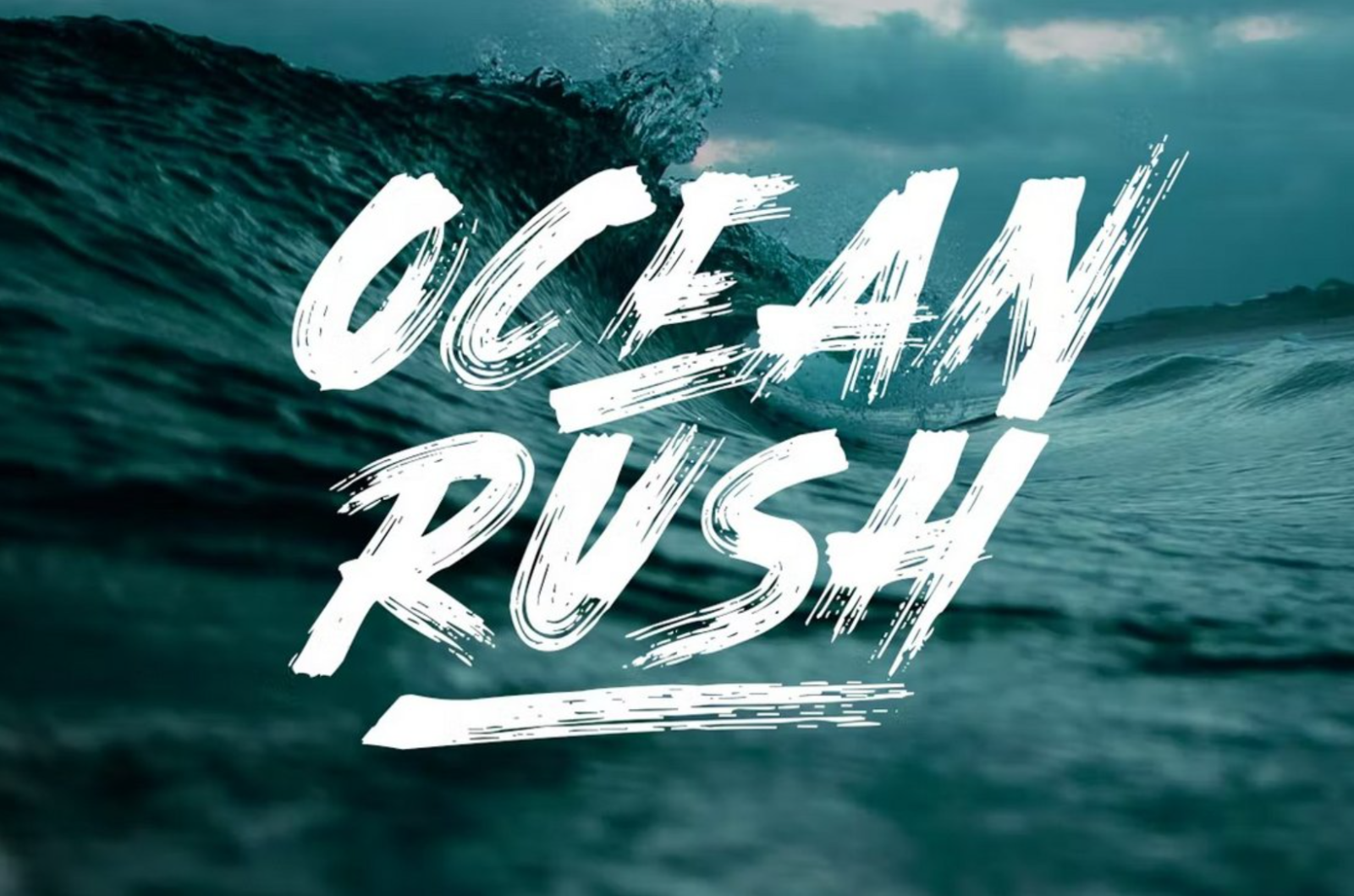
10 Font Viết Tay "Chất Lừ" Không Thể Thiếu Trong Thiết Kế Của Bạn
Dù bạn là người mới bước vào nghề hay là designer kỳ cựu, những font chữ viết tay “chất phát ngất” này chắc chắn sẽ khiến bạn không thể rời mắt. Tham khảo ngay danh sách và làm mới thư viện font của bạn!
Trong thế giới thiết kế đầy màu sắc, font chữ luôn đóng vai trò then chốt quyết định phong cách và cảm xúc của sản phẩm. Trong đó, font chữ viết tay (handwritten fonts) ngày càng được ưa chuộng khi mang đến sự cá tính, ấm áp và gần gũi. Một nét chữ vẽ tay không chỉ giúp thương hiệu của các bạn có dấu ấn riêng biệt mà còn truyền tải cảm xúc chân thật và tự nhiên hơn. Bài viết này, SaDesign sẽ giới thiệu tới bạn Top 10 font viết tay phổ biến nhất hiện nay, kèm theo tiêu chí lựa chọn cũng như mẹo phối hợp và nguồn tài nguyên để bạn có thể tự tin “rinh” về và sử dụng ngay trong thiết kế của mình. Hãy cùng khám phá nhé!
1. Tiêu chí lựa chọn font chữ viết tay
Trước khi điểm qua 10 font nổi bật, chúng ta cần hiểu những yếu tố then chốt giúp đánh giá và lựa chọn một font viết tay phù hợp:
Tính dễ đọc (Readability)
Một font viết tay có thể rất đẹp, nhưng nếu đọc không rõ trên các kích thước nhỏ hoặc nền phức tạp, nó sẽ mất đi giá trị thiết kế. Hãy ưu tiên những font có độ tương phản đủ, nét chữ rõ ràng để người xem không phải “vất vả” khi đọc.
Phong cách (Style)
Font viết tay rất đa dạng: từ nét tròn vui tươi, casual năng động đến các chữ nghiêng thanh lịch, tinh tế. Việc xác định phong cách của dự án ví dụ: trẻ trung, nữ tính, sang trọng hay tối giản sẽ giúp bạn thu hẹp lựa chọn nhanh chóng.
Độ đa dụng (Versatility)
Một font tốt nên hỗ trợ đầy đủ ký tự Latin (bao gồm cả dấu tiếng Việt), có nhiều trọng lượng (weight) hoặc biến thể (italic, bold) để dễ kết hợp khi cần nhấn mạnh.
Phù hợp với brand identity
Không phải font nào đẹp cũng phù hợp với nhận diện thương hiệu. Hãy cân nhắc tính cách và giá trị cốt lõi của thương hiệu: font viết tay nên phản ánh được tinh thần đó, tránh “lệch pha” khiến thiết kế trở nên thiếu tính nhất quán.
Khả năng phối hợp (Pairing)
Một font viết tay thường đi cùng một font serif/sans-serif để tạo tương phản. Khi phối font, hãy thử nghiệm tỷ lệ kích thước, cách canh lề và khoảng cách chữ (tracking/leading) để đảm bảo hài hòa.
2. Top 10 font chữ viết tay phổ biến nhất
Dưới đây là danh sách 10 font viết tay được nhiều Designer ưa chuộng, kèm mô tả, ứng dụng và nguồn tải để bạn dễ dàng “rinh” về dự án:
2.1. Amber Queen Signature
Amber Queen Signature là font viết tay Unicode mang tinh thần khám phá, hòa trộn giữa nét handcrafted và hơi thở hiện đại.
Đặc điểm nổi bật:
• Các góc chữ sắc, nét cắt dứt khoát tạo cảm giác cá tính mạnh mẽ.
• Độ nghiêng vừa phải giúp chữ liền mạch, không quá “lạng quạng”.
• Hỗ trợ đầy đủ ký tự Unicode, bao gồm tiếng Việt có dấu.
Ứng dụng gợi ý:
• Logo cá nhân, chữ ký số hóa trên website.
• Tiêu đề poster, bìa sách về du lịch, khám phá.
2.2. Leah Gaviota Hand Lettered
Leah Gaviota Hand Lettered là bộ font đa dạng, kết hợp giữa chữ đậm, sans‑serif và script để tạo nên phong cách độc đáo.
Đặc điểm nổi bật:
• Bao gồm nhiều biến thể weight: từ light đến bold.
• Chữ sans-serif tạo khối rõ ràng, script mềm mại uốn lượn.
• Thiết kế linh hoạt, dễ dàng mix & match.
Ứng dụng gợi ý:
• Thiết kế bộ nhận diện thương hiệu (brand identity).
• Tiêu đề website, slogan quảng cáo.
2.3. Buffalo Handwritten
Buffalo Handwritten nổi bật với sự đa năng, phù hợp hầu hết phần mềm như Photoshop, Illustrator.
Đặc điểm nổi bật:
• Nét chữ dày vừa phải, đường cọ đậm đều.
• Bố cục ký tự cân đối, dễ đọc trên cả nền đơn sắc và texture.
• Hỗ trợ tính năng OpenType: ligatures, stylistic alternates.
Ứng dụng gợi ý:
• Thiết kế social media posts, Instagram Stories.
• Tạo quote image cho Facebook, Pinterest.
2.4. Beatrix Signature
Beatrix Signature là font viết tay tập trung vào sự cá nhân hóa, với đa dạng độ dài ký tự và phong cách.
Đặc điểm nổi bật:
• Mỗi glyph đều có các biến thể ngắn dài, cho phép Designer điều chỉnh linh hoạt.
• Nét chữ mềm mại nhưng vẫn giữ được cấu trúc rõ ràng.
• Phù hợp cho chữ ký điện tử hay tiêu đề sản phẩm.
Ứng dụng gợi ý:
• Bao bì mỹ phẩm, chai nước hoa.
• Nhãn mác quần áo, túi xách cao cấp.
2.5. Gineva Script
Gineva Script là font viết tay kết hợp nét thư pháp châu Âu, lý tưởng để làm nổi bật tiêu đề.
Đặc điểm nổi bật:
• Đường nét thanh thoát, có sự tương phản giữa nét mảnh và nét đậm.
• Liên kết chữ mềm mại, tạo hiệu ứng dòng chảy uyển chuyển.
Ứng dụng gợi ý:
• Tiêu đề poster, băng rôn quảng cáo.
• Ảnh bìa tạp chí, brochure sự kiện.
2.6. Amstenia Typeface
Amstenia Typeface chiếm cảm tình với phong cách cọ giản dị, thân thuộc.
Đặc điểm nổi bật:
• Nét brush thô ráp nhẹ, từng ký tự cho cảm giác “handmade”.
• Độ dày biến đổi tự nhiên, tạo độ chân thực cao.
• Hỗ trợ đầy đủ ký tự La‑tinh và dấu tiếng Việt.
Ứng dụng gợi ý: